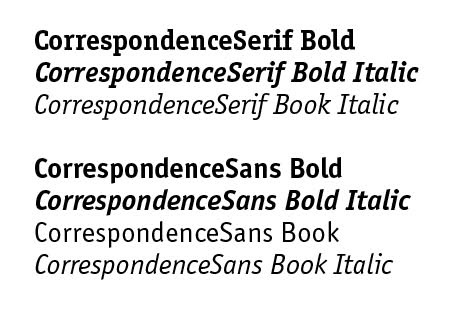
Ich habe ein kleines Problem. Ich habe eine Schriftart namens Correspondence bei mir gefunden. Diese habe ich in den Schnitten Sans und Serif. Nun habe ich folgendes Problem. Als Hersteller finde ich bei dem Schnitt folgende Angabe "Corp. 1992 MetaDesign BigFun Division". Da ein mir bekannter Gestalter gerne diese Schrift kaufen würde habe ich also versucht mich zu erkundigen ob und wo man sie kaufen kann. Ich finde allerdings nur eine Correspondence von Erik Spiekermann (aus dem Jahr 1996) ... die wäre prinzipiell auch ok ... allerdings brauche ich diese Schrift unbedingt auch als Serif und da bin ich bisher nicht fündig geworden.
Das ist Spiekermanns ITC Officina; „Correspondence“ war deren Arbeitstitel.
Der Herstellername Deiner Schrift klingt übrigens für mich ziemlich nach Raubkopie.
Vielen Dank für die schnelle Antwort. Ich bin bei meiner Schriftdatei auch etwas stutzig geworden und habe keine Ahnung wo ich sie überhaupt her habe *chaos und verwirrung herrscht* ... ich hab sie jetzt jedenfalls erstmal verbannt und werde sie freudigst durch die ITC Officina ersetzen.
Soweit ich mich erinnere ist die Correspondence eine
modifizierte Officina von Alexander Branczyk die
nie für den Verkauf gedacht war. Das dürfte auch die
Herstellerangabe erklären.